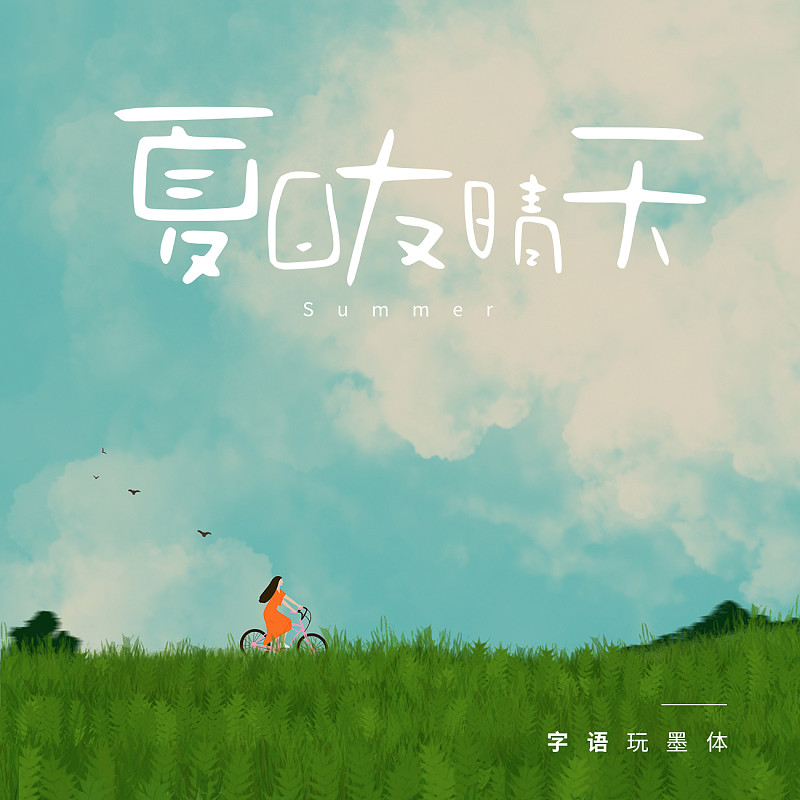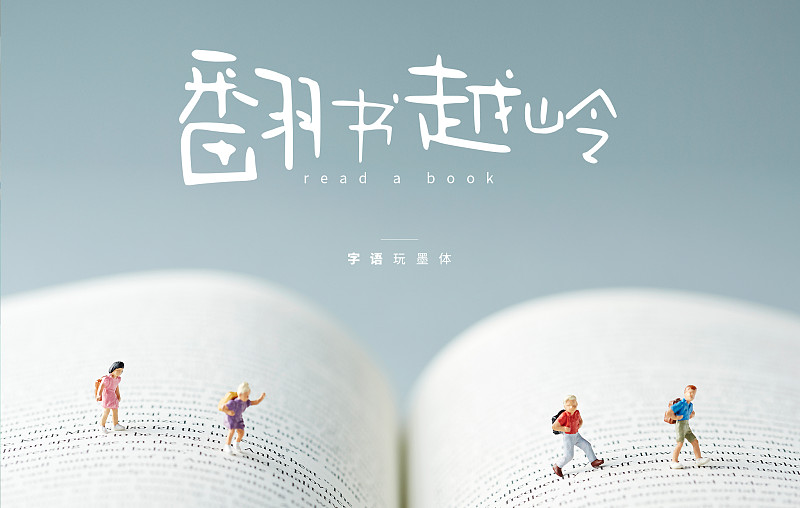
字語(yǔ)玩墨體
這是一款卡通風(fēng)格的創(chuàng)意手寫字體,將字體中所有的口字刻意放大,所有的轉(zhuǎn)折也做圓弧處理,顯得簡(jiǎn)單可愛(ài)。中宮略大,增加字面,結(jié)構(gòu)多變的同時(shí)又保持重心不變,具有良好的展示效果。適用于兒童類的書(shū)刊,品牌廣告和產(chǎn)品包裝設(shè)計(jì),以及社交網(wǎng)絡(luò)的個(gè)性化用字,還可勝任簡(jiǎn)短的正文排版。